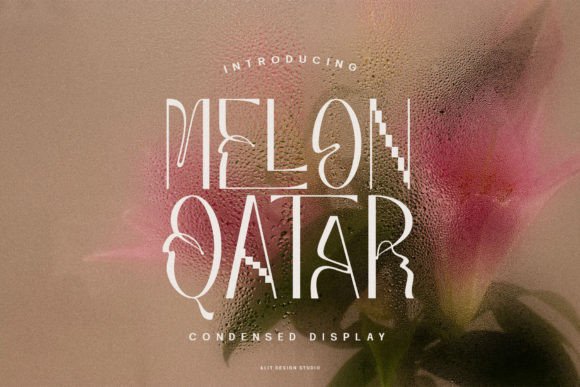
Melon Qatar
Melon Qatar – A Fonte Sans‑Serif Alta que Transforma Seu Design
Se você busca uma tipografia que una elegância contemporânea e alta versatilidade, Melon Qatar chega como a escolha certeira. Criada com linhas alongadas e formas sofisticadas, essa fonte sans‑serif destaca‑se imediatamente em projetos que exigem presença marcante e estilo refinado.
- Estrutura alta e imponente – Ideal para títulos, pôsteres e branding que precisam chamar atenção.
- Formas alongadas e fluidas – Cada glifo possui um toque único que rompe com o padrão dos sans‑serif tradicionais.
- Caracteres alternativos com efeito ondulado – Pequenas variações que trazem dinamismo e ritmo ao texto.
- Passos harmoniosos – O espaçamento interno foi cuidadosamente calibrado para garantir legibilidade sem perder a estética.
- Ligaturas exclusivas – Conexões perfeitas entre letras, proporcionando um fluxo visual suave e coeso.
Por que usar Melon Qatar?
Melon Qatar se destaca em branding, logotipos, design editorial e publicidade porque combina:
- Impacto visual – A altura da fonte cria uma presença dominante que captura o olhar em segundos.
- Flexibilidade criativa – As opções de caracteres alternativos e ligaturas permitem variações sem precisar mudar de família tipográfica.
- Leitura clara – Mesmo com seu estilo distinto, a fonte mantém alta legibilidade em tamanhos maiores.
- Estilo moderno – O design clean e as linhas elegantes alinham-se às tendências de design minimalista e de luxo.
Aplicações Ideais
Use Melon Qatar nos seguintes contextos para maximizar seu impacto:
- Headlines de revistas de moda e lifestyle
- Cartazes de eventos culturais e festivais
- Identidade visual de marcas premium
- Campanhas de publicidade digital e impressa
- Design de embalagens que precisam transmitir sofisticação
Em resumo, Melon Qatar oferece uma fusão única de modernidade, elegância e funcionalidade. Seja para criar um logotipo que se destaque ou para dar vida a títulos impactantes, esta fonte garante um visual forte, fluido e memorável. Se você ainda não experimentou, agora é a hora de inserir Melon Qatar no seu próximo projeto e sentir a diferença que uma tipografia verdadeiramente distinta pode fazer.